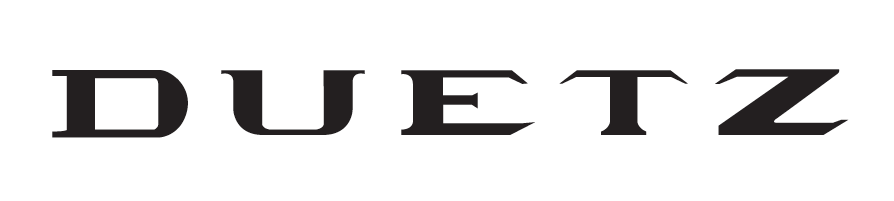
Suche diesen Font des Duetz-Logos
über Hinweise zu möglichen auch kostenpflichtigen Schrifttypen bin ich sehr dankbar. Mir liegen leider nur noch Pfade des Logos, welches ich selbst entworfen habe, vor.
Hallo Ralf, ja ich denke auch, wir haben es ausgehend von irgendeinem Font, in Pfaden modifiziert, letztes Jahr. Ich dachte nur, es erkennt jemand die Ursprungsschrift. Vielen Dank!
Ich hab‘s auch schon horizontal gequetscht weil‘s irgendwie gezerrt aussieht und bei WTF versucht – hat nur sehr entfernte Ergebnisse gebracht :-?